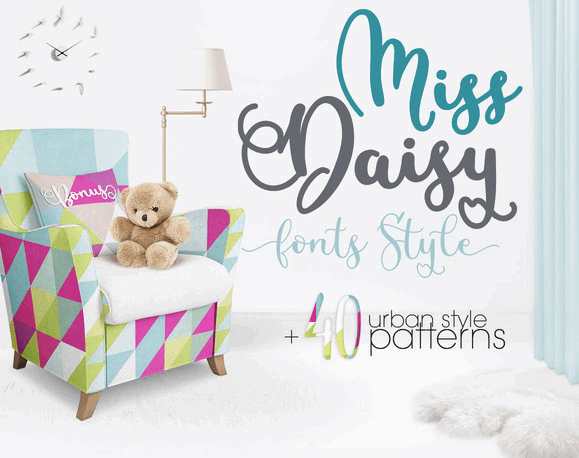
Miss Daisy Script Font – Download Grátis
Descubra Miss Daisy Script Font, uma elegante fonte brush script desenvolvida para designers que buscam transparência e sofisticação em suas criações digitais. Ideal para projetos como logomarcas e identidade de marca, convites de casamento, embalagens de produto, arte digital, e até mesmo postagens nas redes sociais, Miss Daisy oferece um toque elegante que irá realçar qualquer projeto. Ideal para quem busca uma fonte monolinia com um estilo tipográfico suave e fluido, a fonte está disponível em duas tonalidades: suave (bordão) e leve. Além disso, há dois estilos adicional de salsichas para fornecer mais flexibilidade ao criar design criativo. Miss Daisy é perfeita para designers que desejam incorporar uma sensação humana e autêntica em seus projetos digitais, seja para o uso no seu próprio projeto pessoal ou mesmo para um trabalho profissional. Com sua facilidade de utilização e incrível estilo, Miss Daisy é a fonte ideal para qualquer designer buscando incorporar uma atmosfera elegante e sofisticada em seus trabalhos.